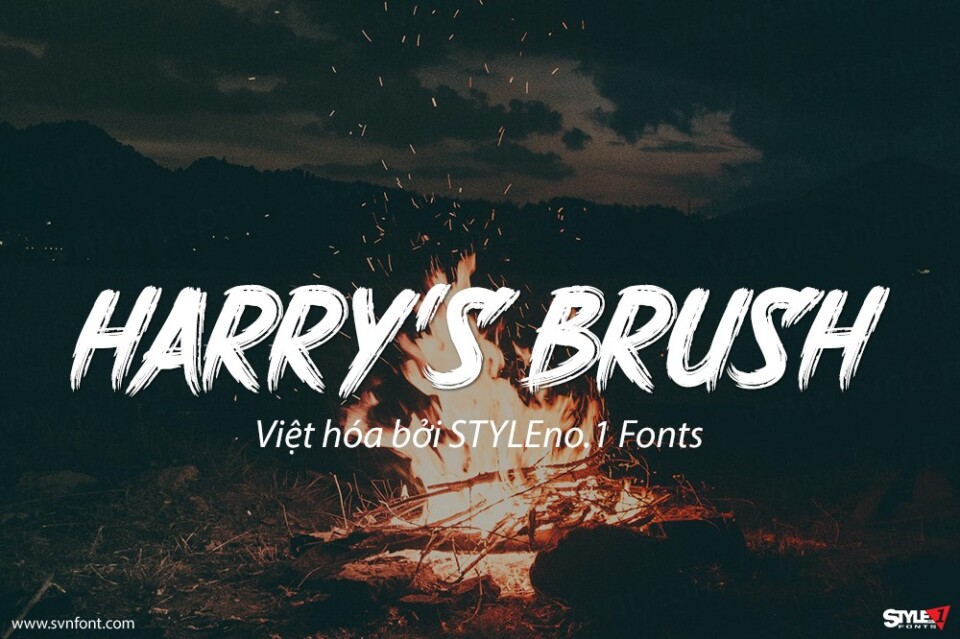
Giới thiệu về Font việt hóa SVN Harry’s Brush
Trong thế giới thiết kế đồ họa, việc tìm kiếm một bộ Font Miễn Phí mang đậm chất nghệ thuật thủ công luôn là ưu tiên hàng đầu của các bạn trẻ và giáo viên. Font việt hóa SVN Harry’s Brush là một minh chứng điển hình cho sự kết hợp hoàn hảo giữa nét cọ vẽ phóng khoáng và sự tinh tế của tiếng Việt. Được chuyển ngữ bởi đội ngũ Styleno.1 Fonts, bộ phông này giúp người dùng dễ dàng truyền tải những thông điệp đầy cảm xúc mà không lo lỗi hiển thị dấu câu.
Đặc điểm nổi bật của phông chữ
Đúng như tên gọi, Harry’s Brush mô phỏng hoàn hảo những đường nét được vẽ trực tiếp bằng cọ sơn hoặc bút lông. Các nét chữ có độ dày mỏng linh hoạt, tạo nên hiệu ứng thị giác mạnh mẽ và sống động cho mọi bản thiết kế. Điểm đặc biệt của Font việt hóa SVN Harry’s Brush chính là tính ứng dụng cao, từ việc trang trí báo tường, làm slide thuyết trình học tập đến thiết kế bìa sách. Sự mộc mạc nhưng đầy cá tính của nó giúp các tác phẩm trở nên nổi bật hơn bao giờ hết.
Cách ứng dụng Font việt hóa SVN Harry’s Brush hiệu quả
Tạo điểm nhấn cho dự án sáng tạo
Với phong cách tự do, phông chữ này cực kỳ phù hợp cho các tiêu đề lớn hoặc câu trích dẫn mang tính truyền cảm hứng. Học sinh có thể dùng nó để làm nổi bật tên đề tài, trong khi giáo viên có thể biến hóa các bài giảng trở nên thu hút và gần gũi hơn. Khi sử dụng Font việt hóa SVN Harry’s Brush, bạn nên ưu tiên các màu sắc rực rỡ hoặc tông màu đất để tăng thêm vẻ chân thực của chất liệu cọ vẽ.
Kết luận và trải nghiệm người dùng